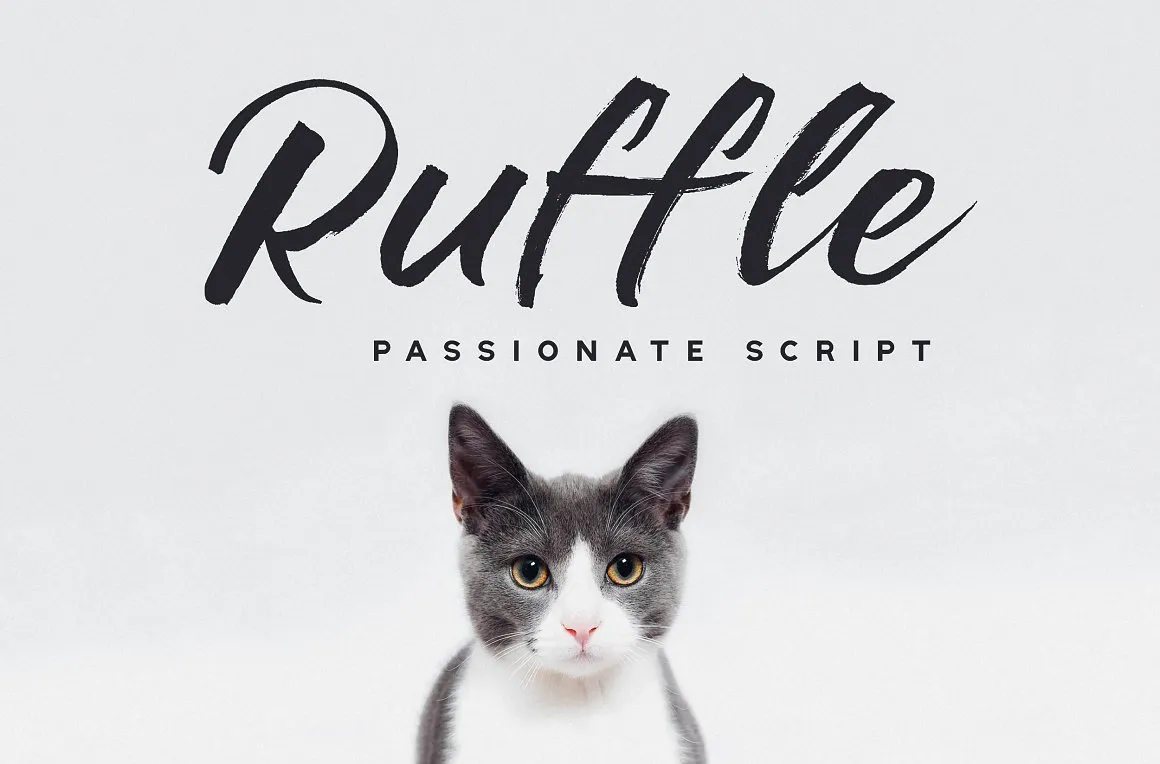
Ruffle Brush Font – Download Grátis
Introduzimos Ruffle, uma fonte criada por Konstantine Studio com um estilo casual e urbano. Essa é uma fonte rústica feita usando um pincel de tinta rápida que mantém um look elegante em cada letra. Este tipo de fonte seria ideal para suas necessidades de marca vintage casual, seja na identidade visual ou nos materiais impressos. Ruffle traz uma vibe jovial e urbaninha ao seu projeto sem deixar de ser sofisticado. É perfeito para quem quer transmitir um estilo vintage moderno em seus elementos gráficos. Se você busca criar algo inovador e contemporâneo, mas ainda quer manter o charme clássico, Ruffle é uma excelente escolha. Esta fonte foi projetada para atender as necessidades de branding vintage dos consumidores urbanos. Ela é perfeita para aqueles que desejam transmitir ao público um tom casual e animado, mas também manter a elegância tradicional que fazem do seu negócio reconhecível na comunidade da moda ou cultura urbana. Com sua fórmula rápida de pintura feita com pincel, Ruffle oferece flexibilidade em termos de tamanho e estilo. É uma escolha ideal para designers que buscam algo mais versátil em suas soluções gráficas. Seja em materiais impressos ou na criação de design digital, você certamente encontrará um uso inovador para esta fonte Ruffle Brush. Seja você um artista ou designer visual, a fonte Ruffle é uma ótima adição à sua coleção de recursos gráficos. Com seu estilo único e eficiente, ela ajudará a garantir que o seu design brilhe no cenário digital atual. Experimente Ruffle hoje e veja como ela pode revolucionar seus projetos!